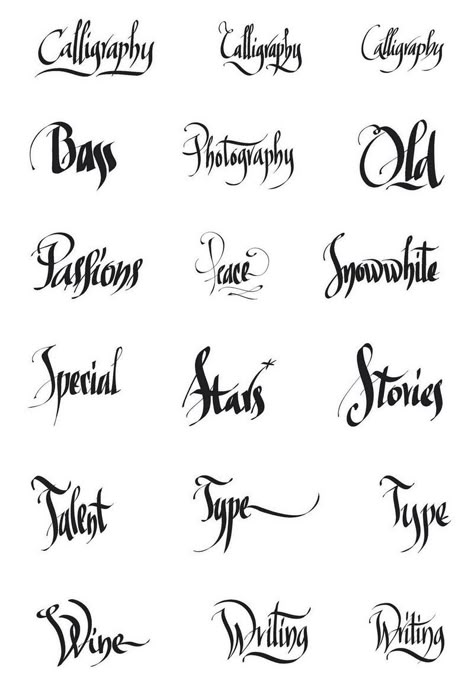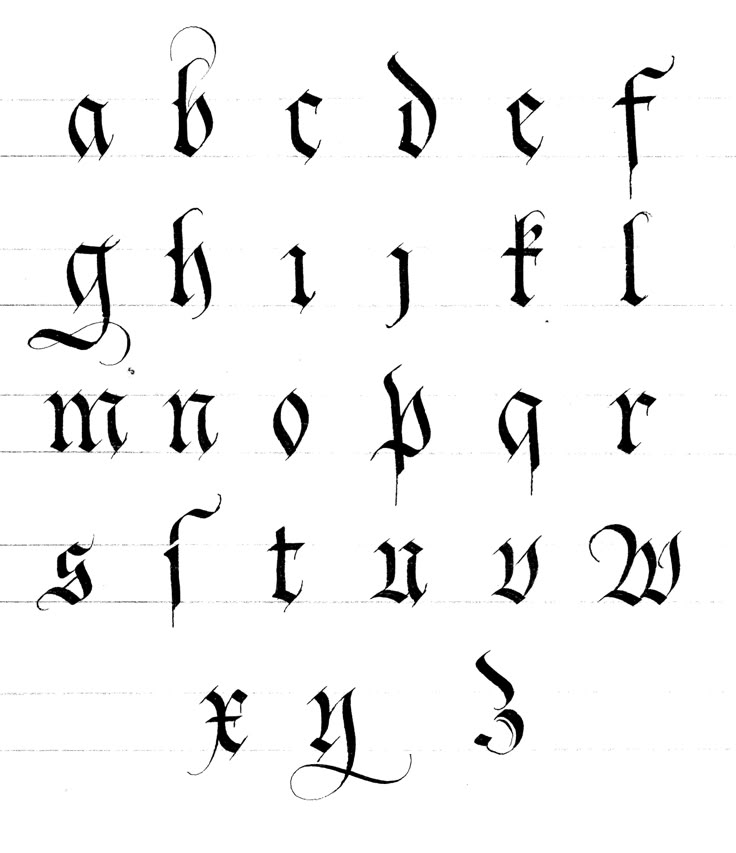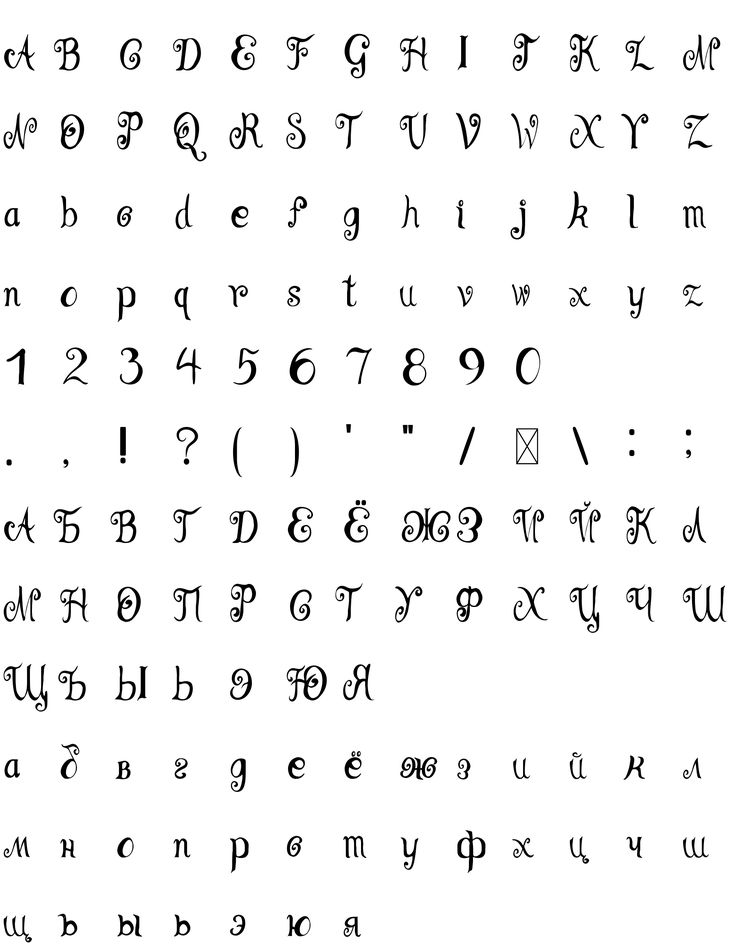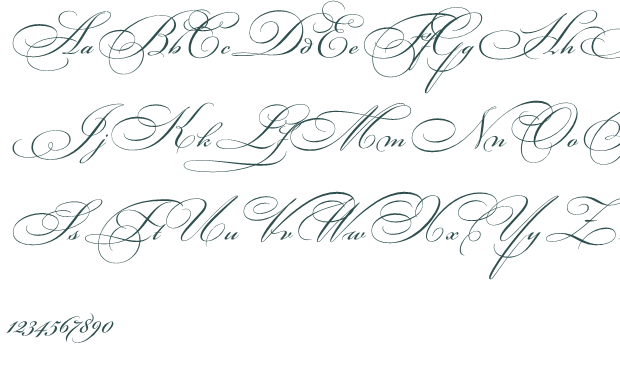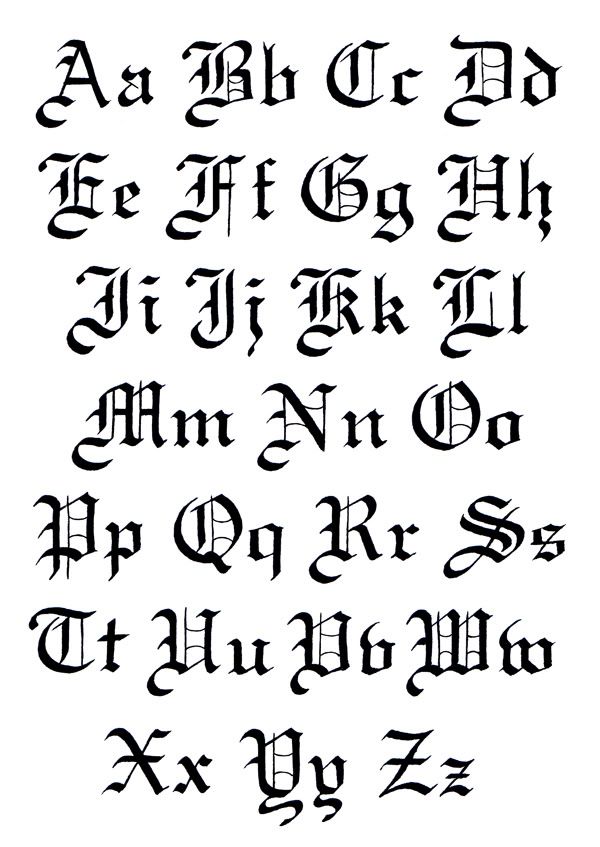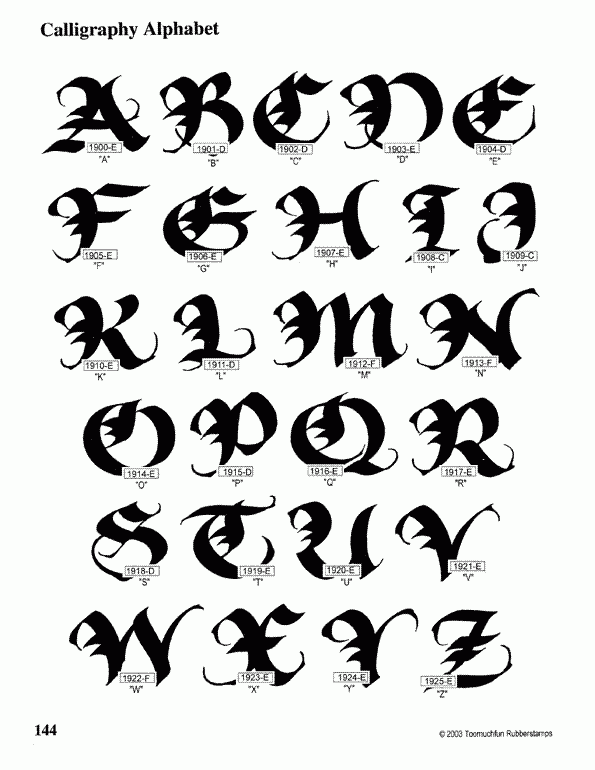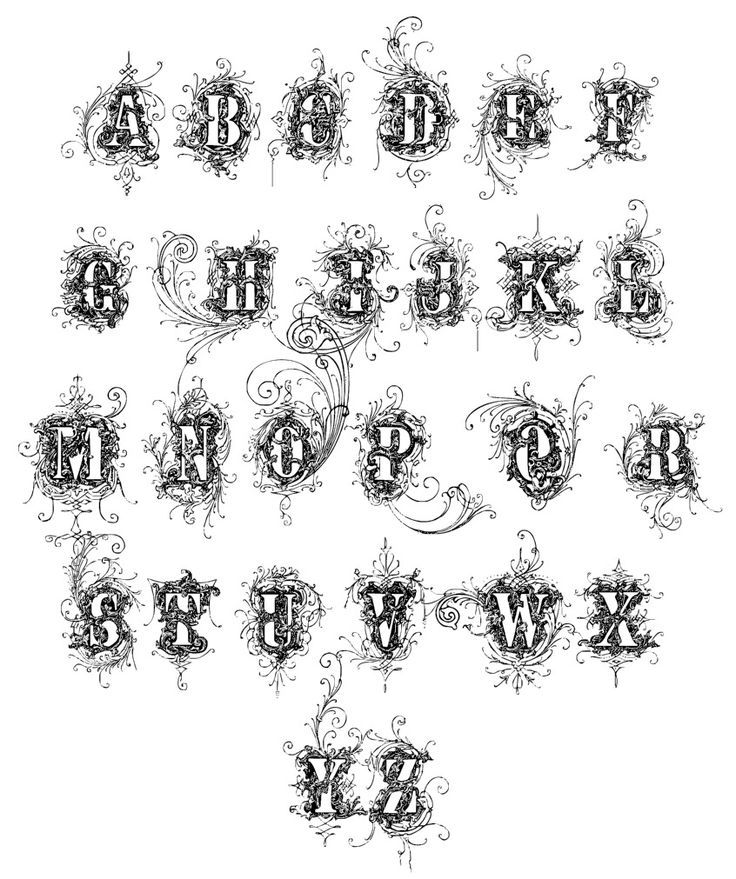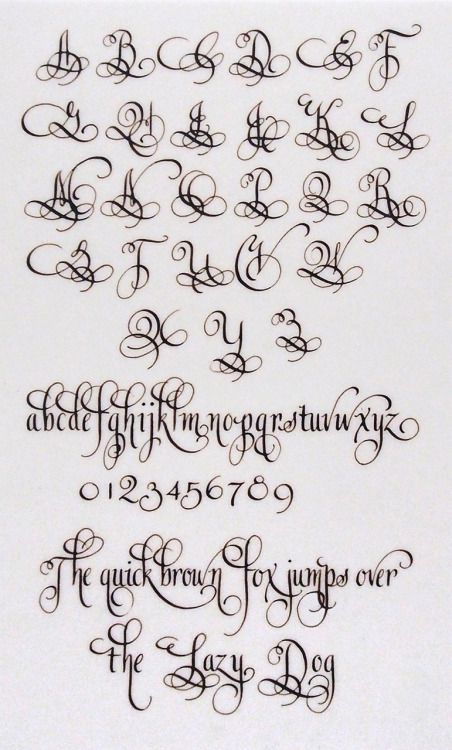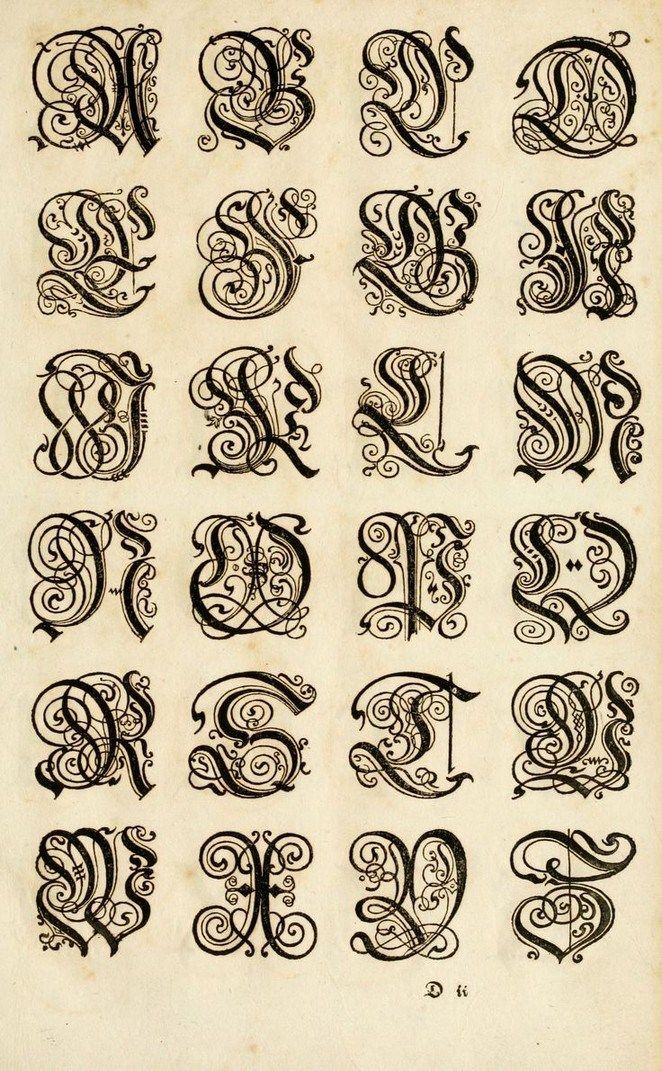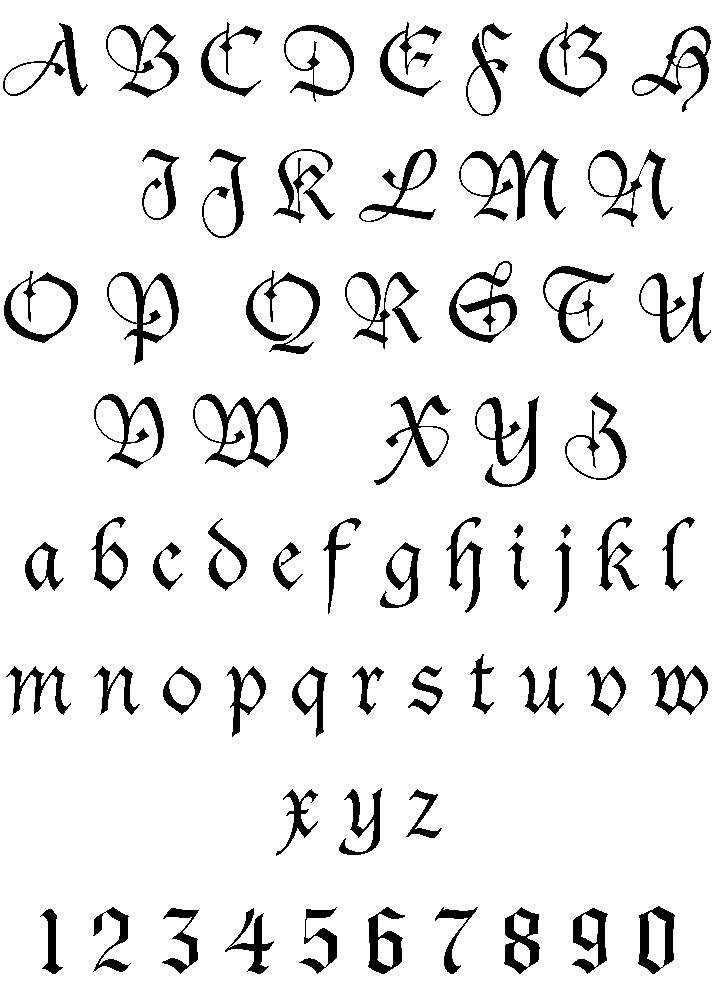
Решили сделать тату с надписью, но все еще не можете выбрать окончательный вариант? Тогда вам обязательно стоит воспользоваться нашим сервисом, позволяющим выбирать шрифты тату онлайн.
Это поможет вам найти оптимальный вариант, поэтому вы придете в тату салон полностью подготовленным. Сегодня шрифты для татуировок могут иметь массу отличий, поэтому каждый может найти для себя нечто уникальное и неповторимое. Тату надписи могут иметь разное предназначение, так как они позволяют по-разному проявить свою фантазию, выбрав романтическую или же философскую фразу.
Шрифты для тату онлайн – это великолепная возможность подобрать идеальную визуализацию для вашего нательного рисунка. Разнообразные фразы и афоризмы имеют огромную популярность как среди мужчин, так и женщин. Учитывая это, женские и мужские тату в форме надписей можно встретить на любом шагу. Шрифты для тату надписей имеют определяющую роль, так как именно от них зависит визуальный эффект того или иного рисунка. Действительно, независимо от содержания, любой нательный рисунок может получить более брутальный или, наоборот, более женственный вид, если изменить шрифт.
Потратив всего несколько мгновений, вы сможете поэкспериментировать с разнообразными вариациями для вашей татуировки. Вы сможете подобрать шрифт для тату онлайн, опробовав популярные стили, оттенки и размеры. Это могут быть как мужские, так и женские тату, которые зачастую отличаются своей стилистикой и предназначением.
На нашем сайте вы найдете оригинальные и красивые шрифты для тату, которые помогут вам подчеркнуть свою индивидуальность. С помощью сервиса вы сможете разобраться не только с шрифтом, но и содержанием, а также длиной фразы. Действительно, тату надписи могут состоять как из одной буквы, так и с целого предложения.
Популярные шрифты для тату надписей
На сегодняшний день существует огромное количество разнообразных шрифтов тату, поэтому каждый сможет найти для себя нечто особенное. Если говорить более конкретно, то наибольший спрос имеют следующие направления:
Каллиграфия. Это течение может иметь массу перевоплощений, так как очень многое зависит от почерка и стиля мастера.
- Готика. Готический шрифт для тату надписей отличается своей популярностью среди неформальной молодёжи. Несмотря на это, он также может иметь массу разнообразных вариантов.
- Граффити. Уникальное сочетание оригинальных шрифтов с урбанистическими изображениями, которое возникло достаточно давно, и их можно встретить на стенах городов всего мира.
- Оригинальные этнические надписи. Каждый народ имеет свои уникальные черты, которые касаются и письменности. Например, арабские шрифты, славянские, романские, израильские и так далее.
- Надписи с эффектом старой печатной машинки. Такие нательные рисунки сегодня имеют огромный спрос, так как они позволяют не забывать прелести прошлого. В данном случае речь идет про отпечатки и визуальные дефекты, которые могли оставаться на бумаге при использовании печатной машинки.
Тату надписи становятся более модными и популярными в наши дни.
Их востребованность объясняется тем, что все больше людей по всему миру выбирают в качестве татуировки не простой рисунок, а текст с глубоким смыслом. Текстовые фразы могут представлять собой важные слова, имена, короткие цитаты или афоризмы, позволяющие продемонстрировать окружающим людям свои взгляды на жизнь. В статье подскажем, какой шрифт для тату можно выбрать парню или девушке, а также, рассмотрим красивые виды надписей в различных стилях.
Как подобрать шрифт для тату?
Подбор шрифтов для тату – долгое и нелегкое занятие. Вообще, в интернете существует множество сайтов и программ, позволяющих подбирать шрифты для тату надписей online. Однако, если вы не хотите встретить другого человека с таким же красивым шрифтом, советуем вам обратиться к мастеру, который разработает стили тату надписей специально для вас. Конечно, за эту услугу придется доплатить, но в итоге, вы получите неповторимые красивые буквы, которые больше ни у кого не найдете.
«В тату-сообществе есть поговорка: жирный шрифт будет держаться. И это правда — даже несмотря на то, что со временем все распространяется, жирные линии, как правило, со временем становятся наиболее разборчивыми», — объясняет Пиньянелли, но отмечает, что опять же, личные предпочтения и талант художника являются ключевыми при принятии этого решения.
«При этом я видел много татуировок с тонкими линиями, которые так красиво зажили и держались годами».